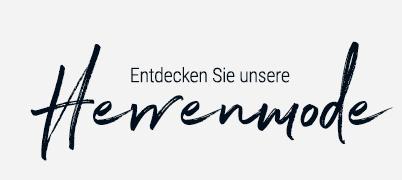
Suche Handschrift in Werbung von Tchibo
ich bin auf der Suche nach der Handschrift, die Tchibo "online" im beigefügten Banner verwendet. Was mein ihr - ist das eine komplette Schrift, oder wurde das "handgezeichnet"?
Könnte man meinen, aber schau Dir mal die drei »e« an – alle identisch! Die rr-Ligatur wiederum ist klasse, wenn’s denn eine Satzschrift ist. Ich denke mal, dass es entweder eine nicht so gut ausgebaute Satzschrift ist (bei der Alternativbuchstaben für die am häufigsten benötigten Buchstaben fehlen). Oder aber, es ist tatsächlich ein handgezeichneter Schriftzug, wobei im Anschluss an das Schreiben mit der Hand die Zeichen am Rechner auseinandergenommen, und die gelungensten neu zusammengesetzt wurden. Die dreimalige Verwendung des identischen kleinen »e« würde dann auf Faulheit schließen lassen … ;-)
Northwell includes 3 font files;
1. Northwell • A handwritten script font containing upper & lowercase characters, numerals and a large range of punctuation.
2. Northwell Alt • This is a second version of Northwell, with a completely new set of both lower and uppercase characters. If you wanted to avoid letters looking the same each time to recreate a custom-made style, or try a different word shape, simply switch to this font for an additional layout option.
3. Northwell Swash • A set of 20 hand-drawn swashes, the perfect finishing touch to underline your Northwell text. Simply install this as a separate font, select it from your font menu and type any A-U character to create a swash.
Ligatures • Are also available for several lowercase characters (double-letters which flow more naturally). These are only accessible via software with opentype capability or a glyphs panel, e.g. Photoshop/Illustrator.
Aha. Also schlecht sortierte Satzschrift. :nicken:
Oder einfach nur schlampig gesetzt – die Northwell in ihren drei Versionen (siehe oben) könnte durchaus verschiedene e an Bord haben …